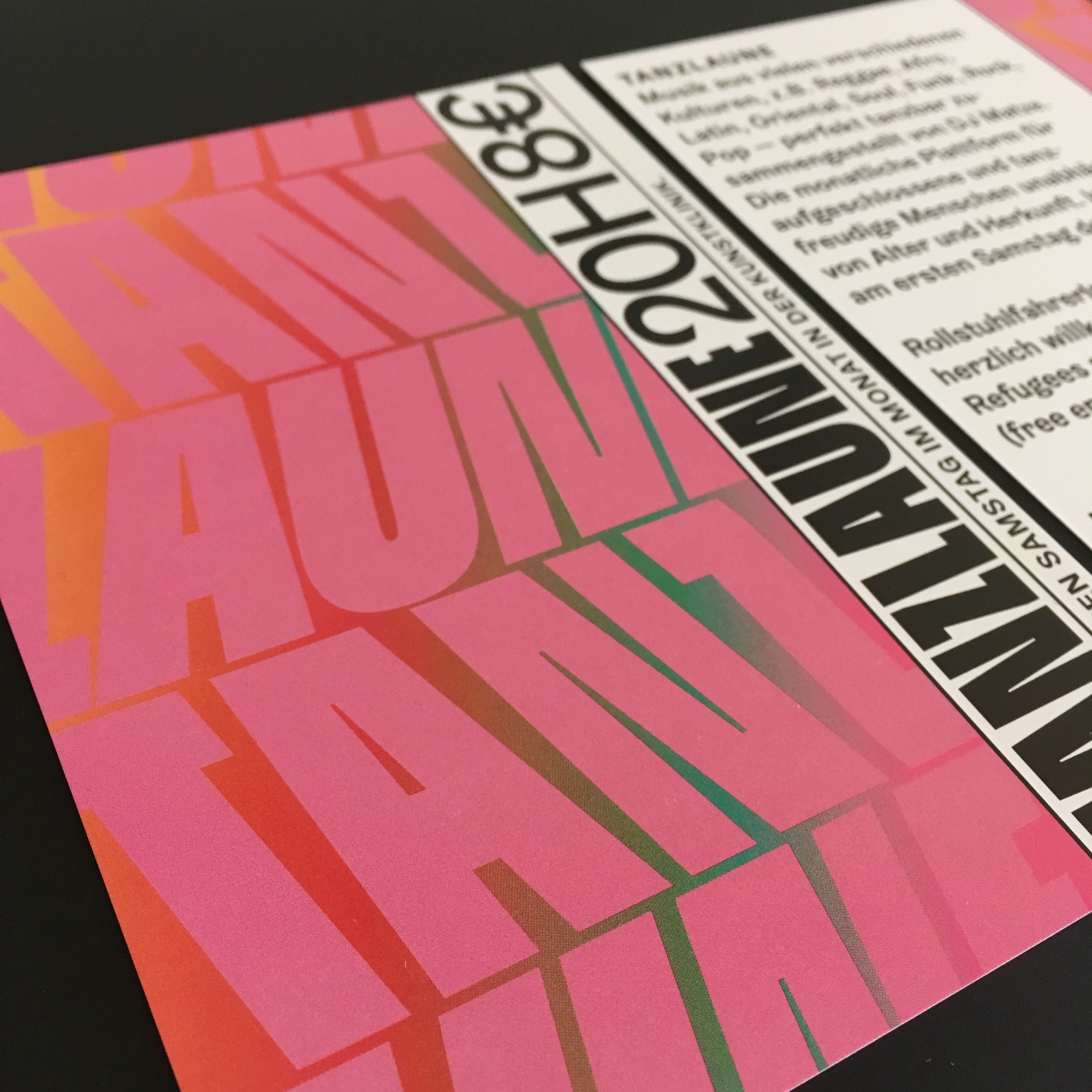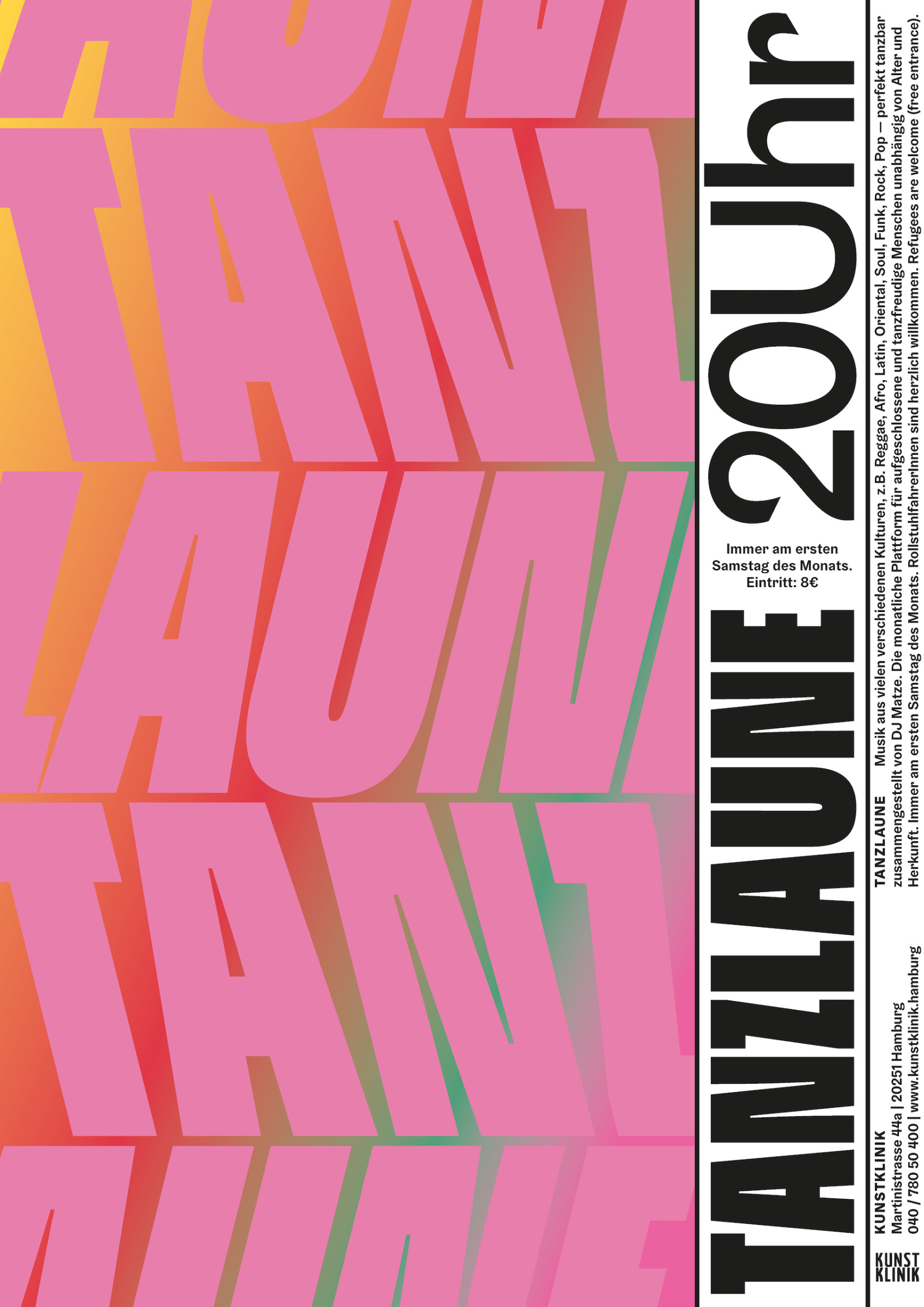
Tanzlaune
Tanzlaune ist eine monatliche Veranstaltung der Kunstklinik Hamburg Eppendorf. Sie vereint Musik aus verschiedenen Kulturen und ist eine Plattform für aufgeschlossene Menschen unabhängig von Alter und Herkunft. Das bunte Plakat stellt die Vielfalt der Veranstaltung dar und wie der Titel vermuten lässt, scheinen die Buchstaben über das Papier zu tanzen.
Schrift: Norbert von Philipp Neumeyer
& Graebenbach von Camelot Typefaces